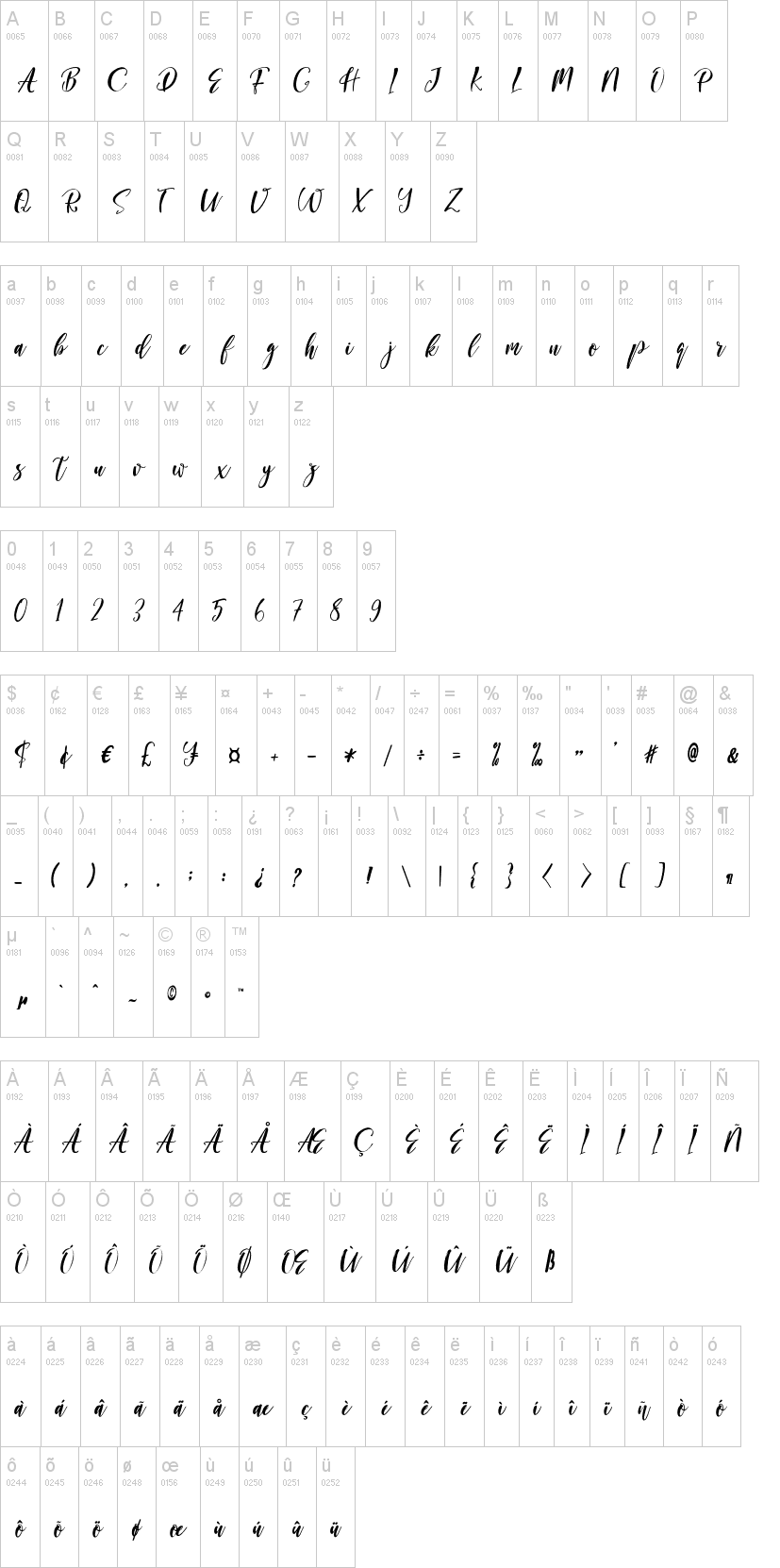
Georgina Script 是一款精美的手写字体,由著名的设计师Alejandro Paul设计。它的风格活泼而温柔,具有良好的可读性,适用于各种文字和平面设计项目,特别是节日卡片、海报、标志等。它的字形具有流畅的线条,细节精致,字体的细节和质感都非常出色,能够提供美观的视觉效果。内容介绍
Georgina Script是一款非常不错的手写艺术字体,具有很好的视觉感,适合于文化类的宣传设计、商业类品牌的广告和产品包装设计以及个性化文字排版等较多场景。